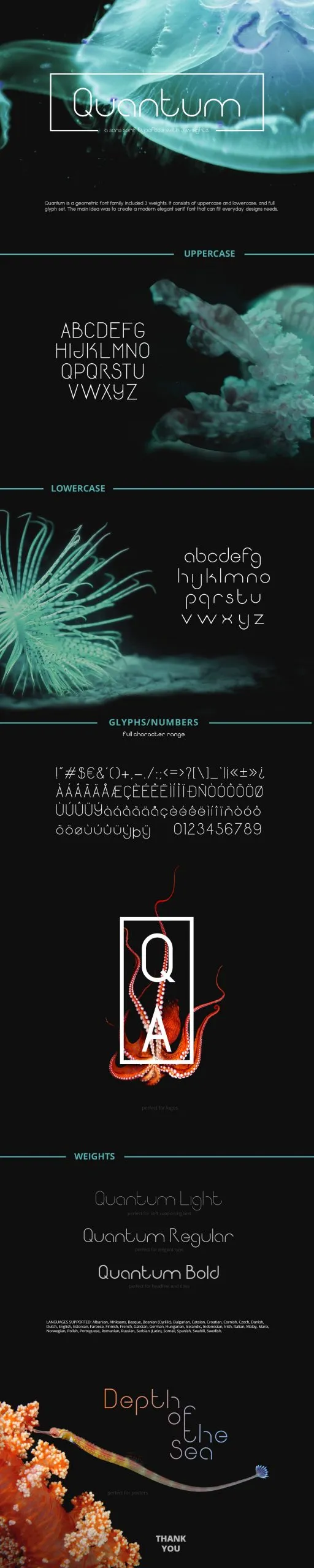
Quantum Font é uma família moderna de fontes geométricas sem serif que combina sofisticação com simplicidade. Essas letras são perfeitas para desafios diários do design, oferecendo uma expressão elegante e minimalista que se adapta a qualquer projeto visual. Suas formas atemporais e linhas retas proporcionam um equilíbrio entre modernidade e clássico, tornando-a uma escolha ótima para designers à procura de uma fonte versátil que combine elegância com função. Hamilton é o responsável pelo design desta família extensa e contemporânea, criada para atender às necessidades do mundo moderno de forma precisa e eficaz. Seja você um profissional ou aficionado pela arte digital, Quantum Font será a escolha certa para dar uma nova vida aos seus projetos de design.